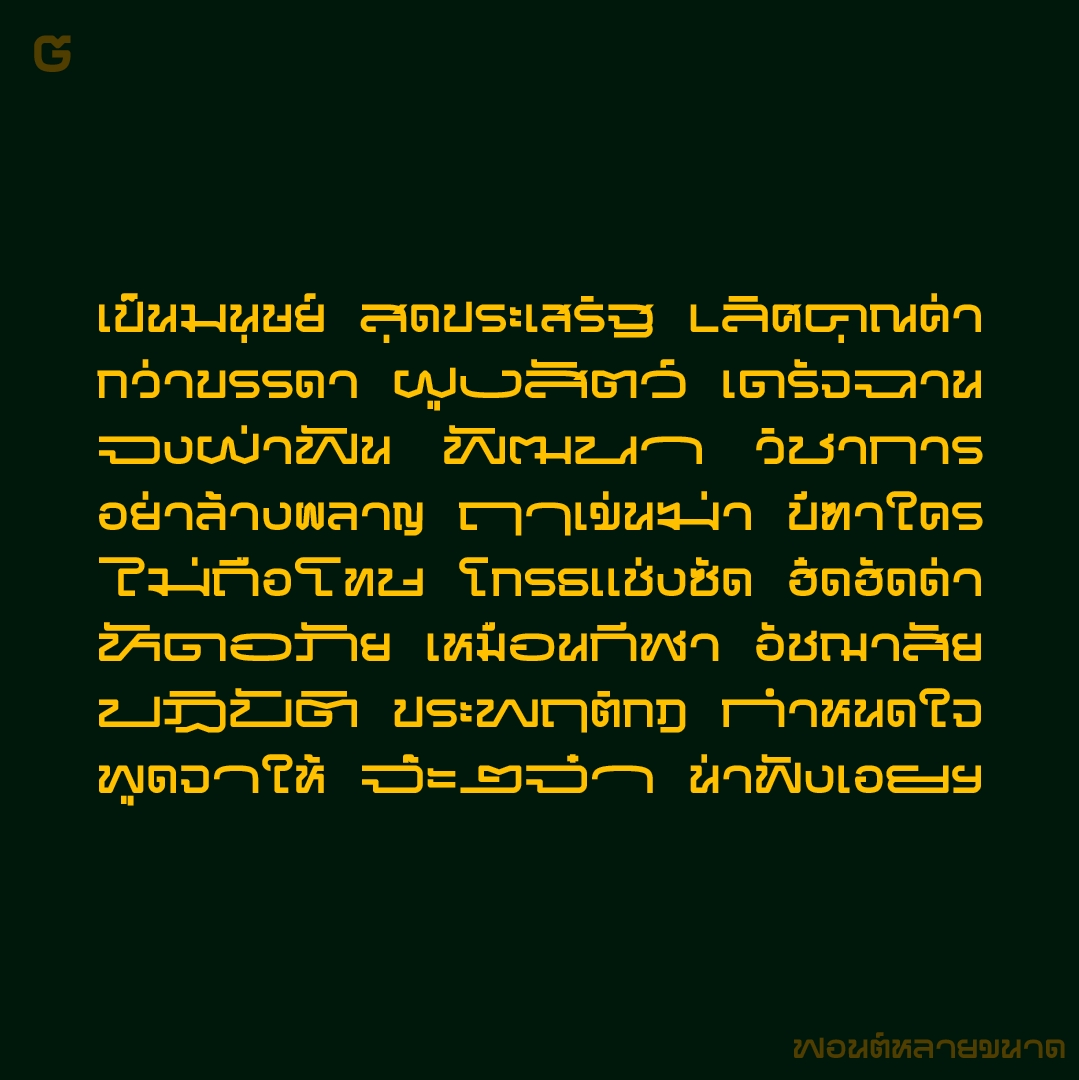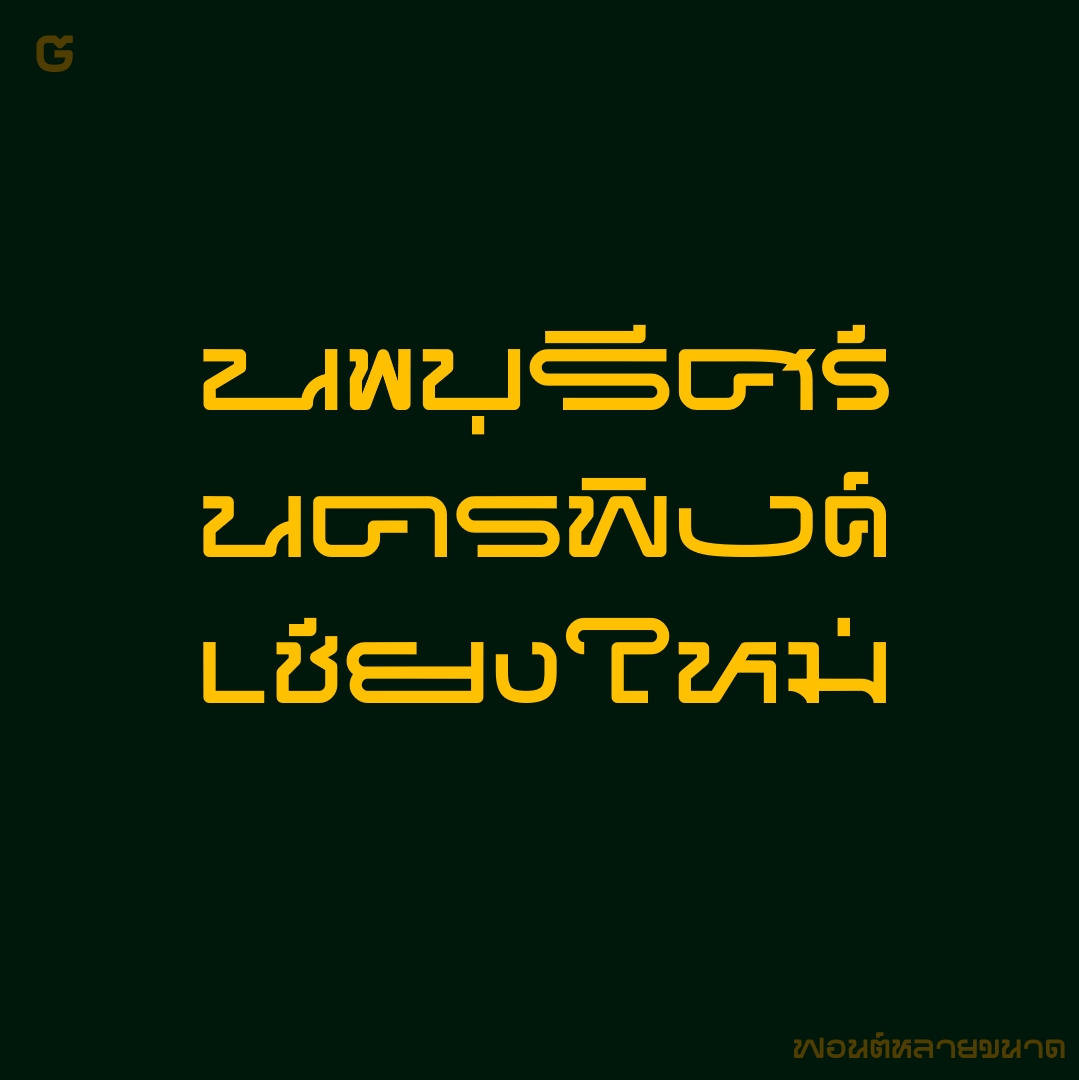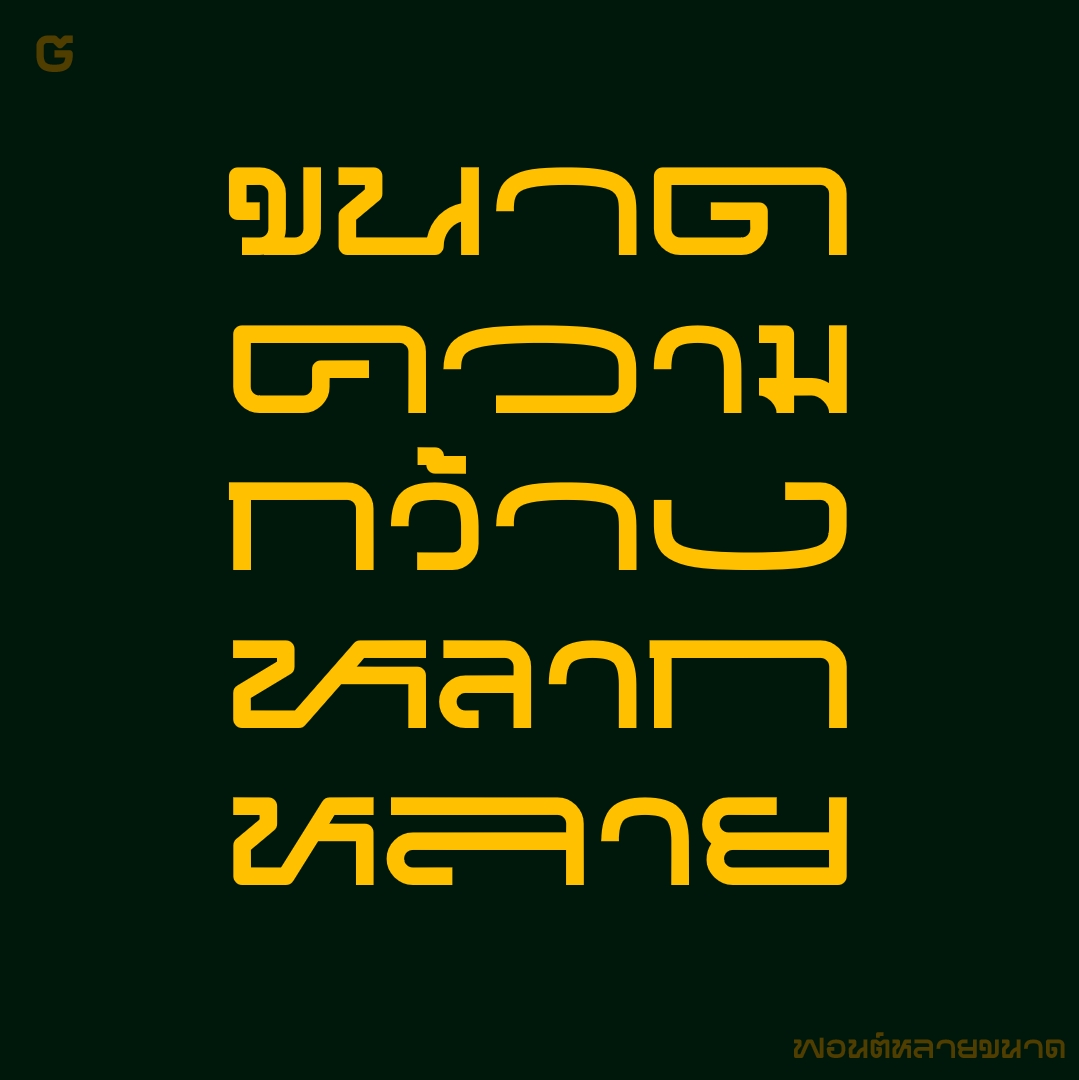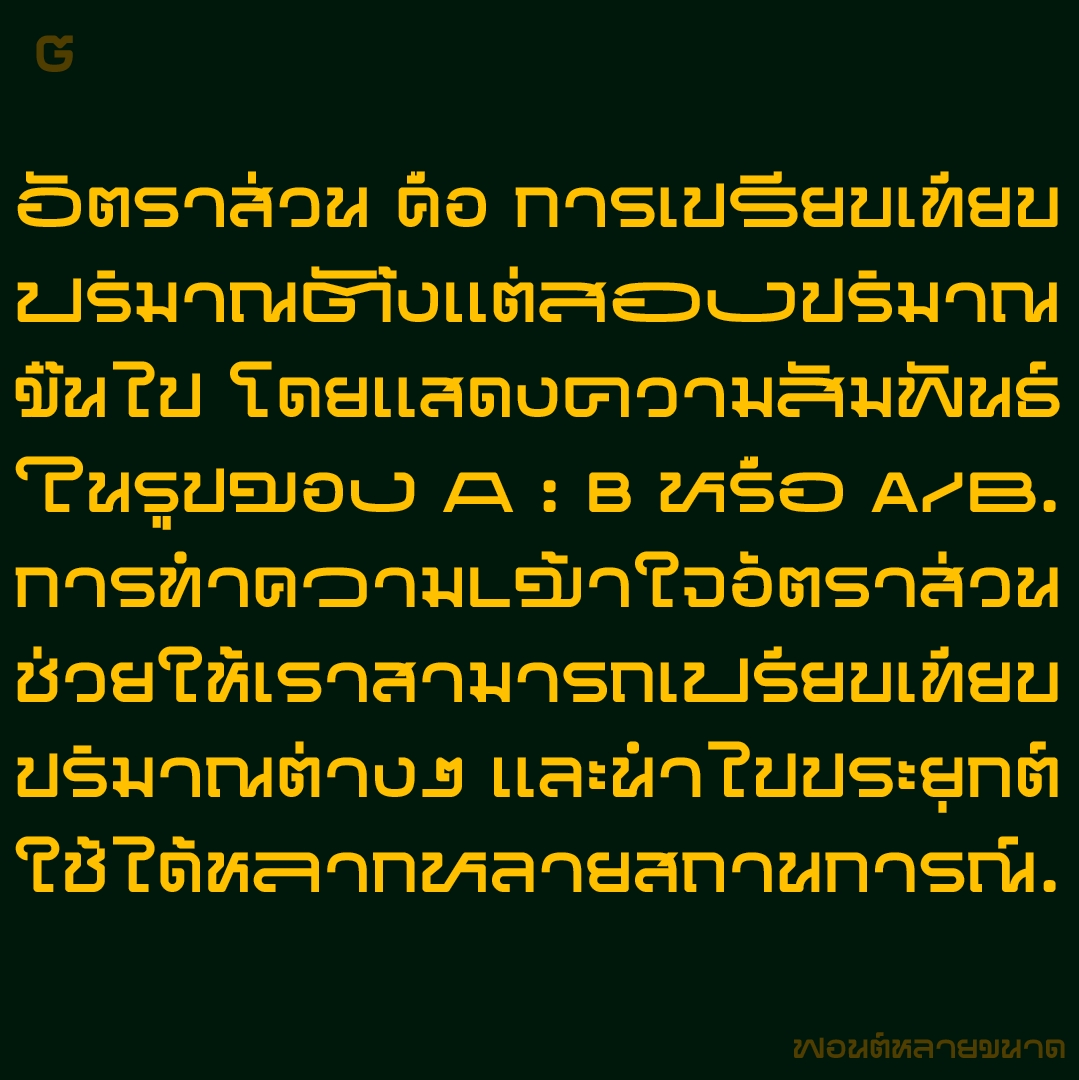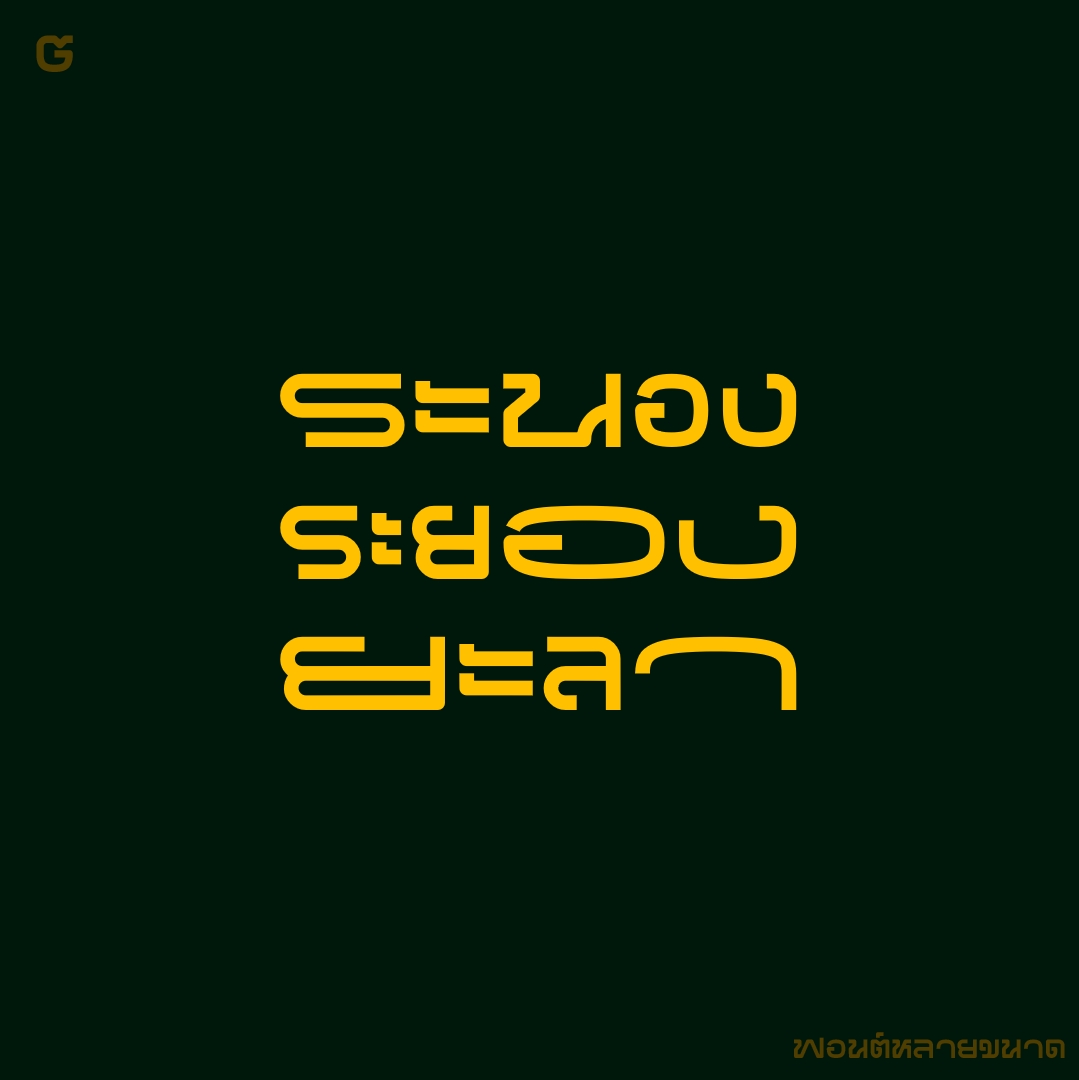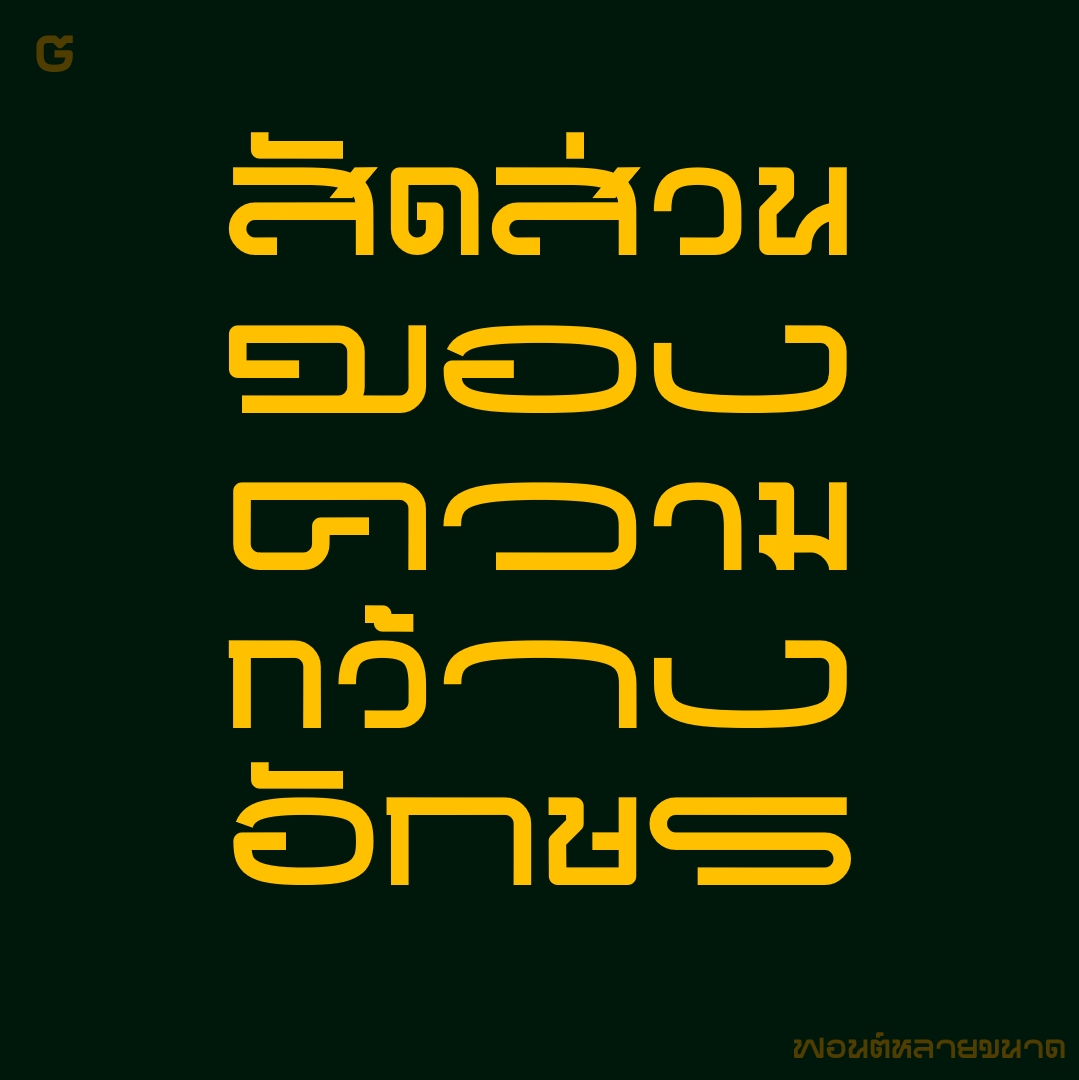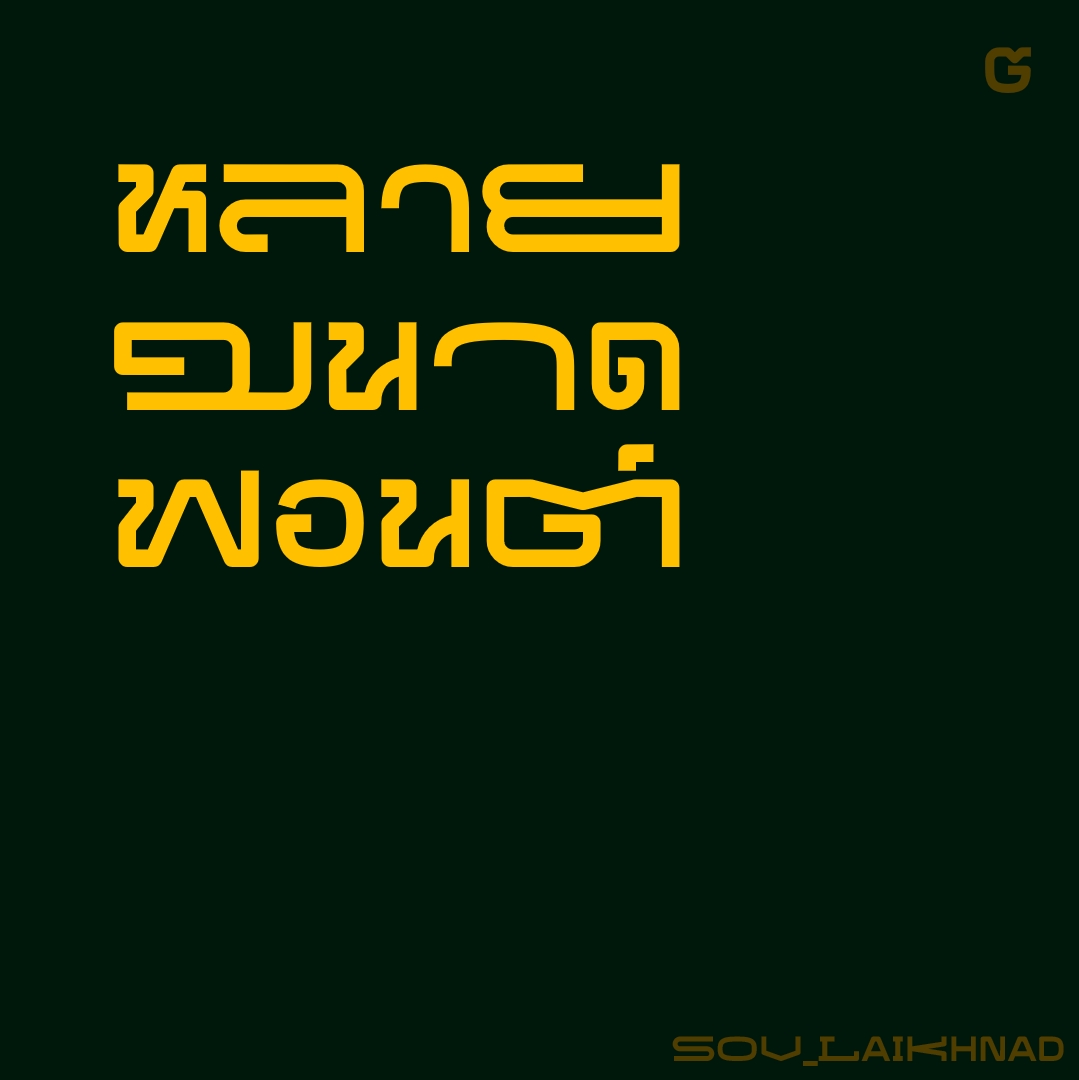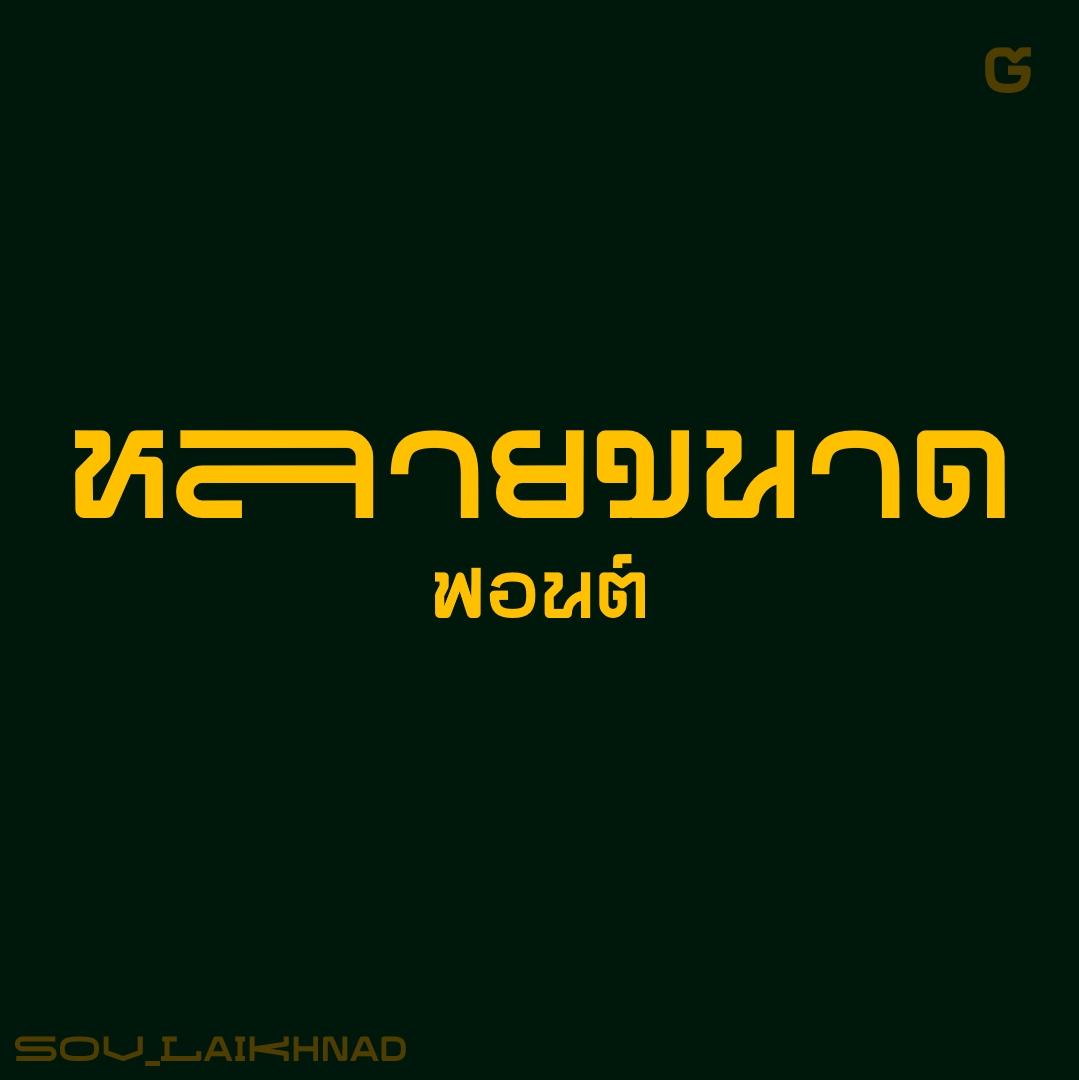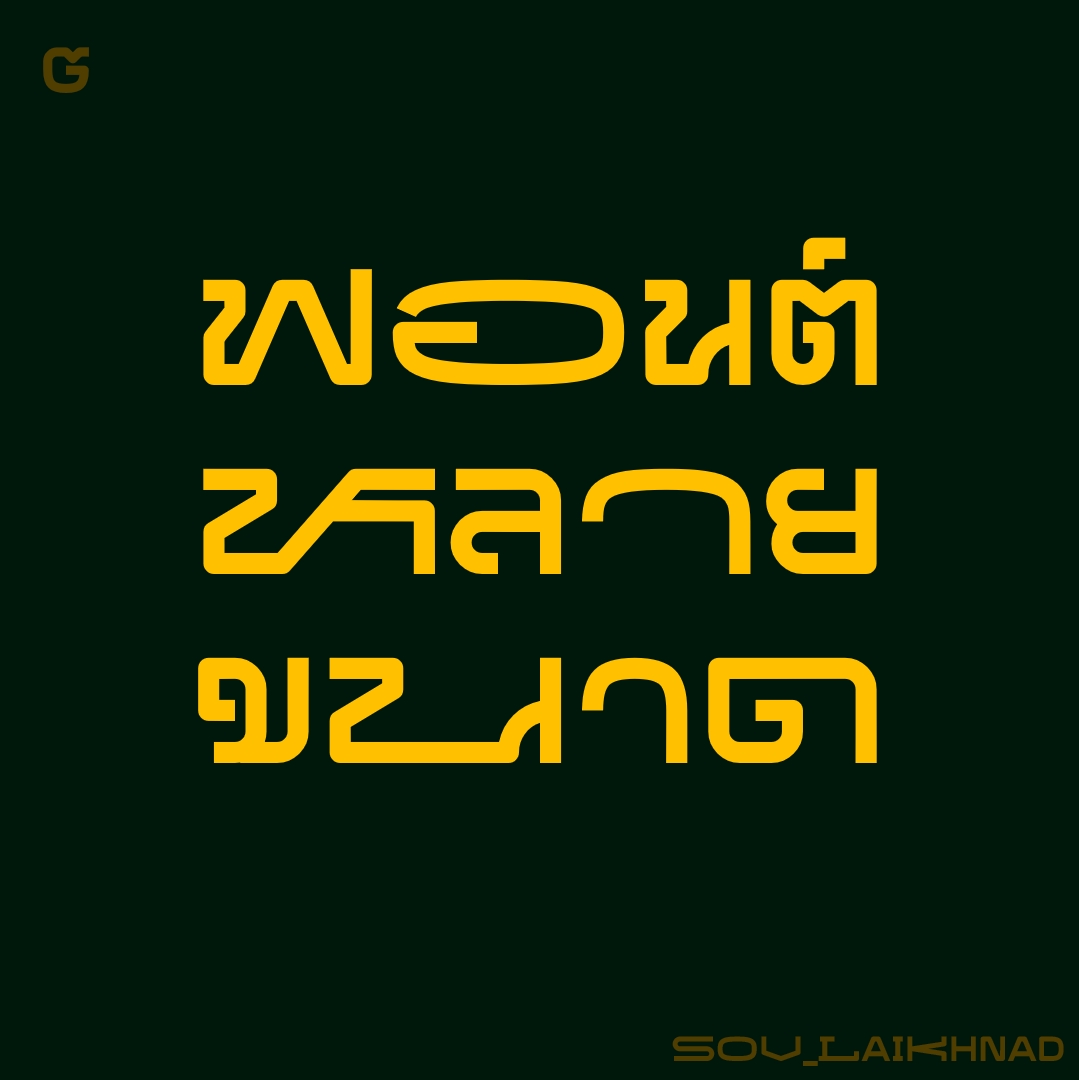
ฟอนต์ หลายขนาด
ฟอนต์หลายขนาด ไม่ใช่ proportional space แต่เป็นอัตราส่วนความกว้าง 2 เท่า 3 เท่า ของ space ตัวหนาใช้เป็น พาดหัว หรือใช้กับ ข้อความหลายบรรทัด แต่ไม่ยาวเกินไป เอาไว้เล่นกับความกว้างตัวอักษร (กด ฯฯ หน้าอักษรที่ต้องการเปลี่ยนความกว้าง)
อย่างเวอร์
1. ขนาดเป็นสัดส่วน ต่อกัน
2. ตัวกว้าง ไม่ใช่ตัวยืด (นอกจากขนาดเส้นแล้ว ยังคุมความยาวเส้นขวาง และความเอียง ให้พอเหมาะ)